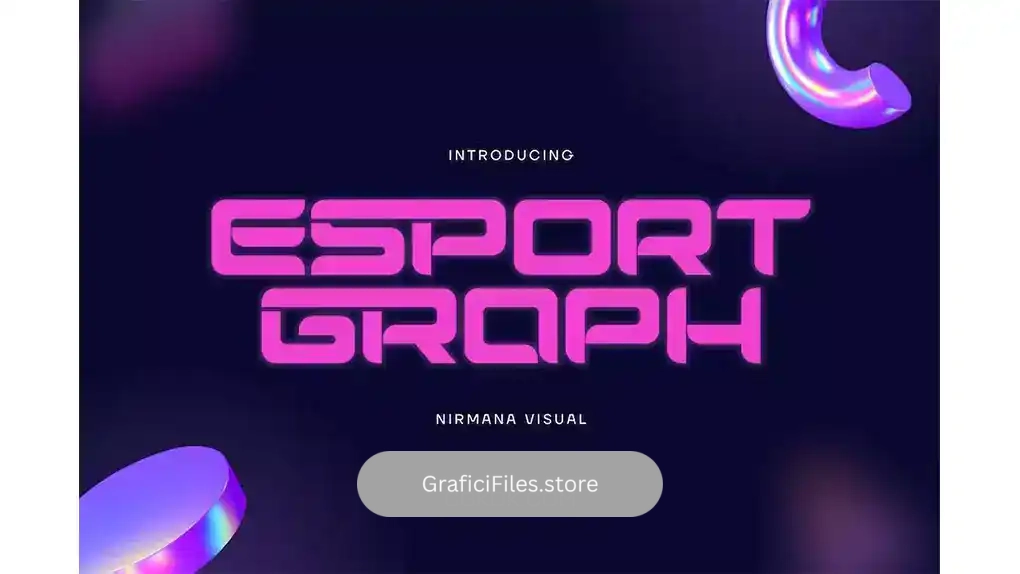
دانلود فونت انگلیسی لوگو Esport Graph – Logo Font
فونت انگلیسی لوگو Esport Graph – Logo Font : این مجموعه شامل یک فونت انگلیسی مدرن است که برای لوگو، برندینگ، تبلیغات، بسته بندی محصول، پست و استوری اینستاگرام و غیره مناسب میباشد.
• عنوان مجموعه: Esport Graph – Logo Font
• سبک: Sans-Serif
• فضا بین حروف: معمولی
• اندازه بهینه: تمامی سایز ها